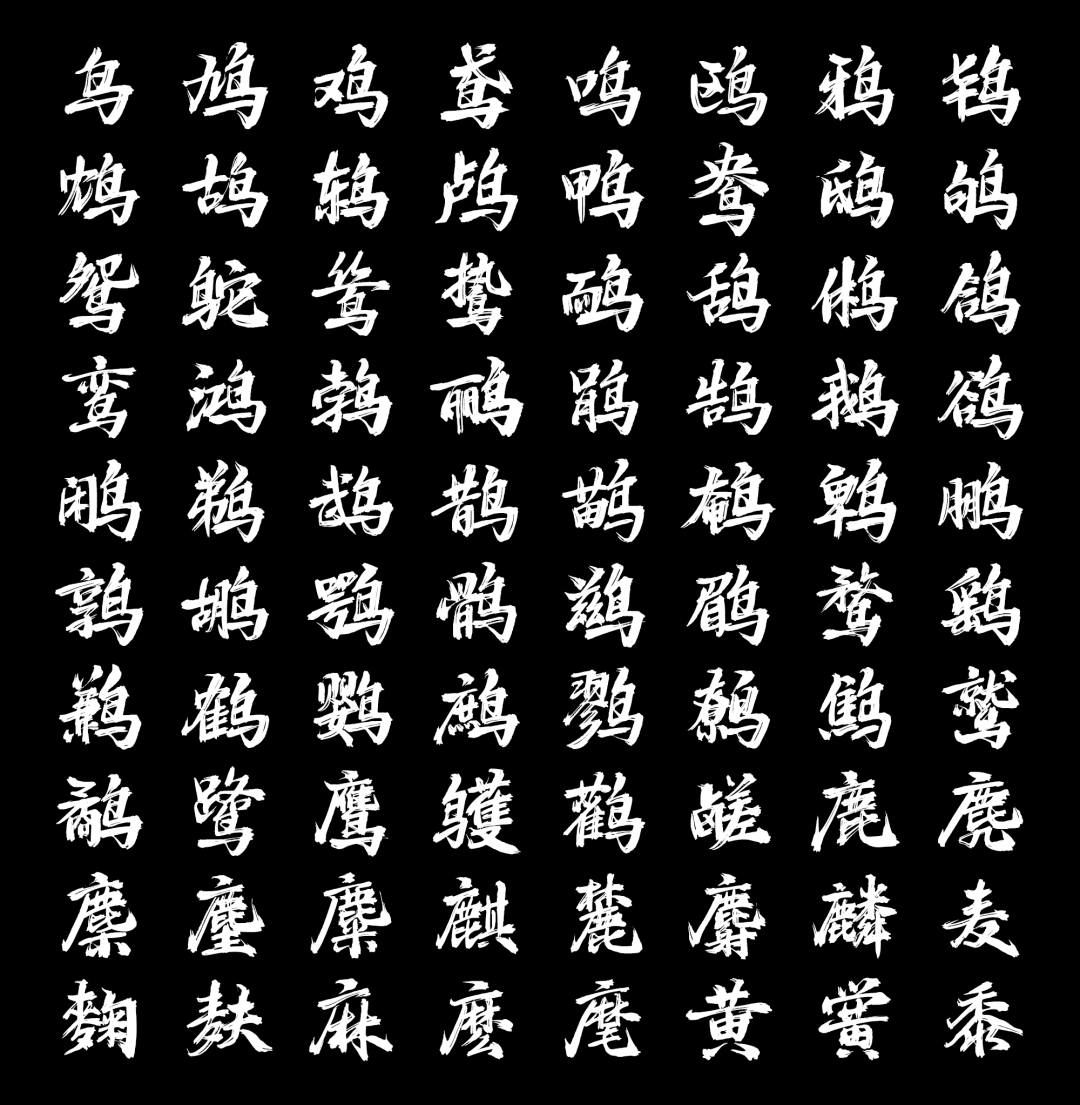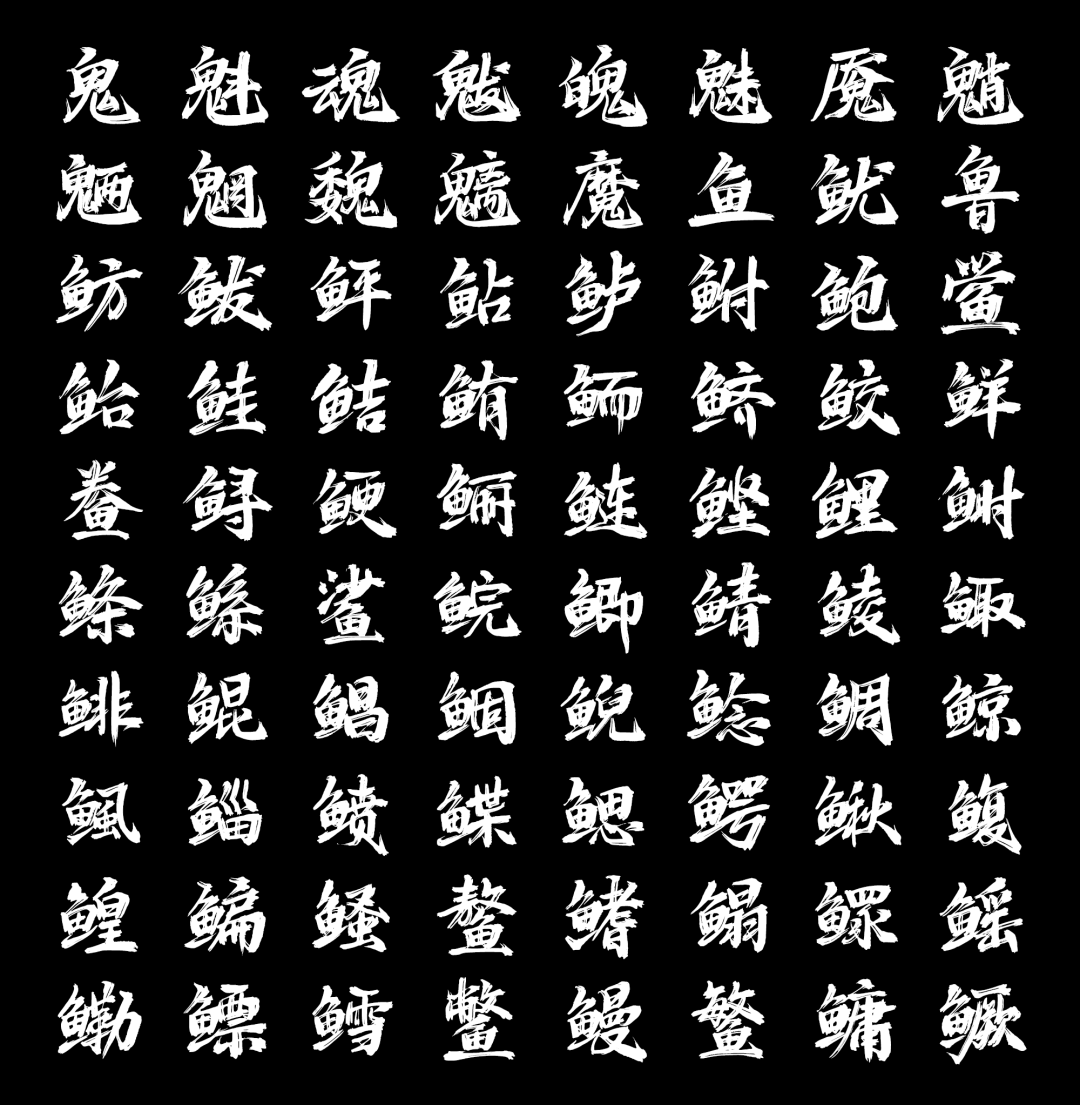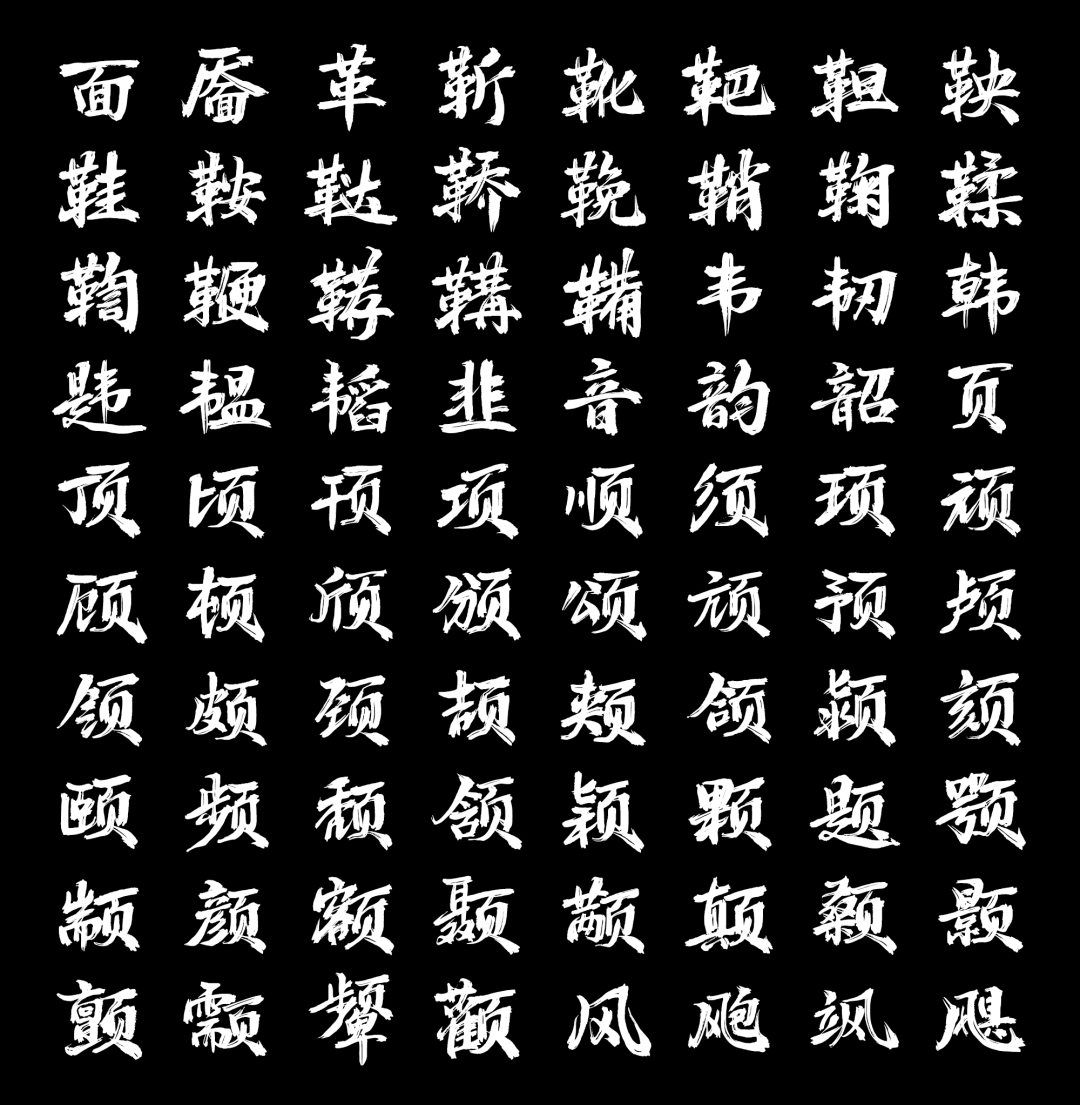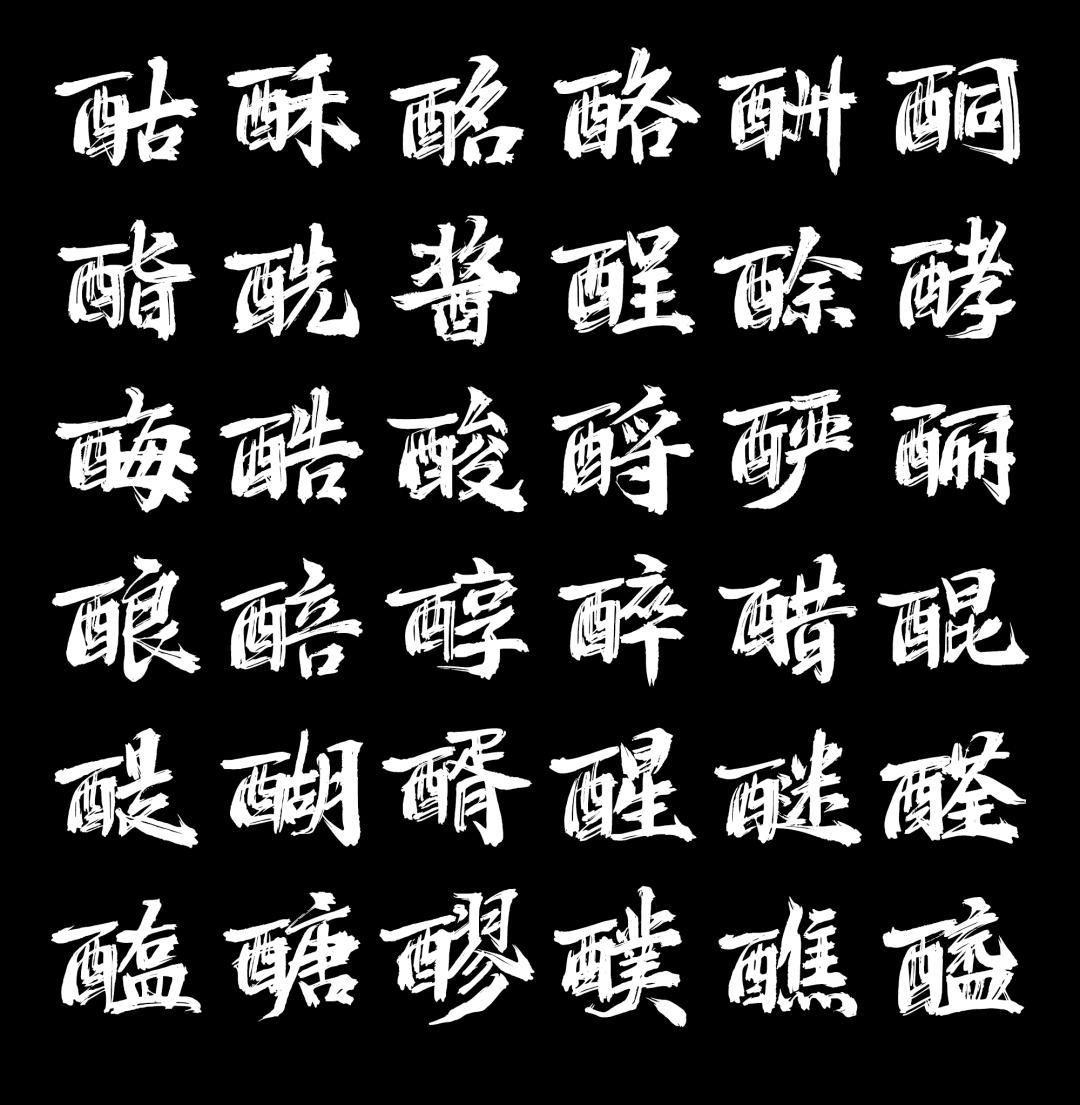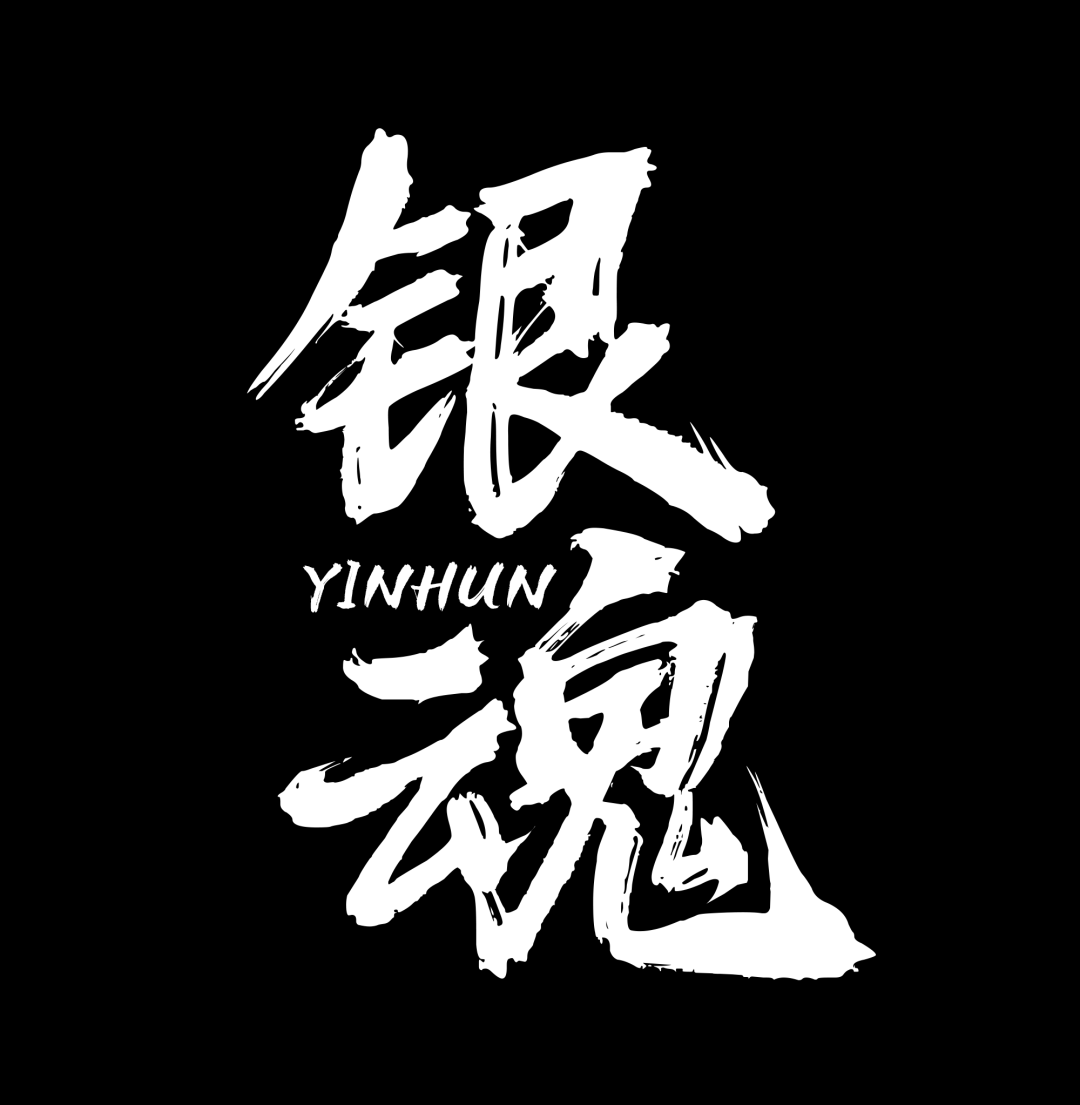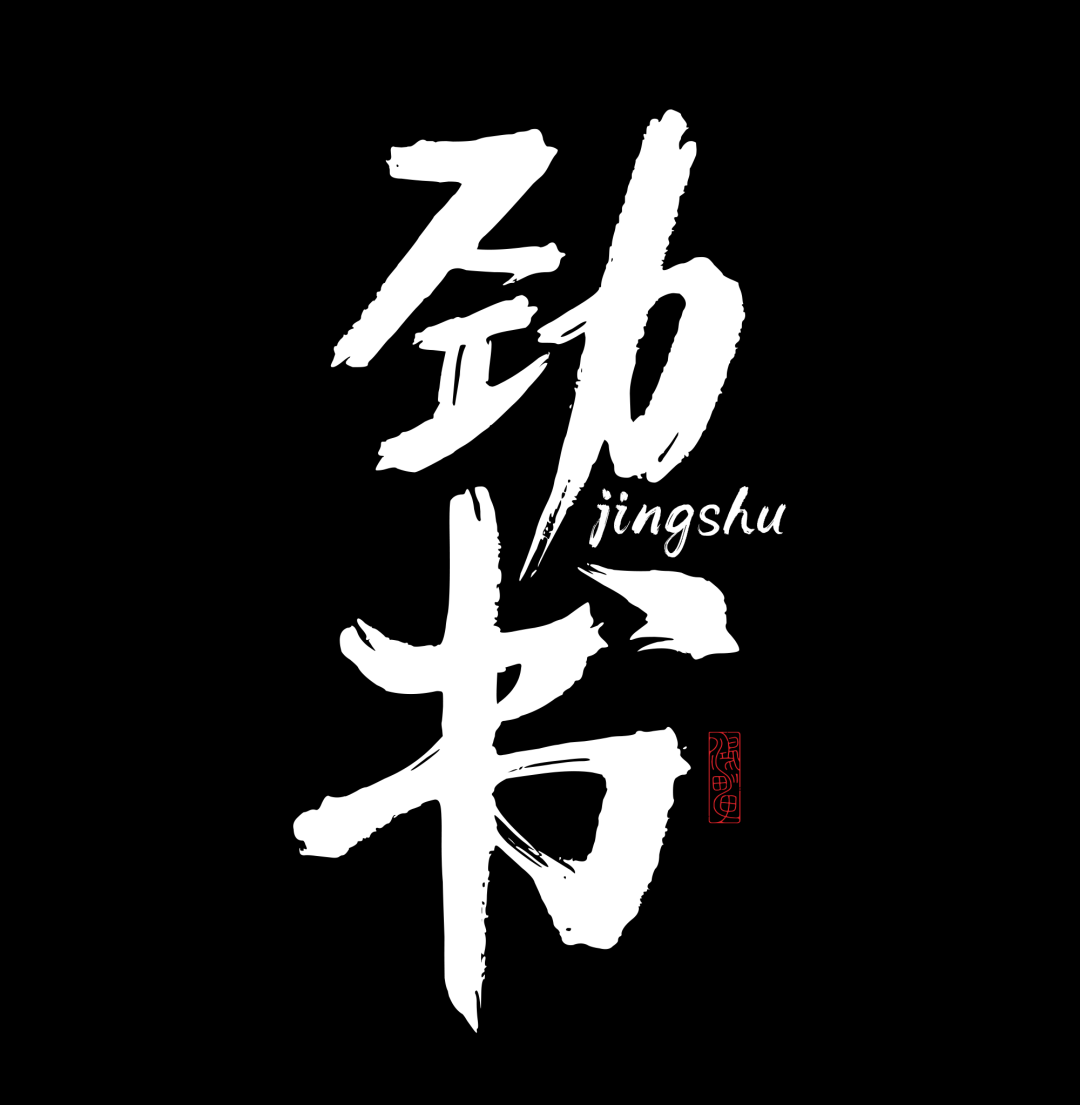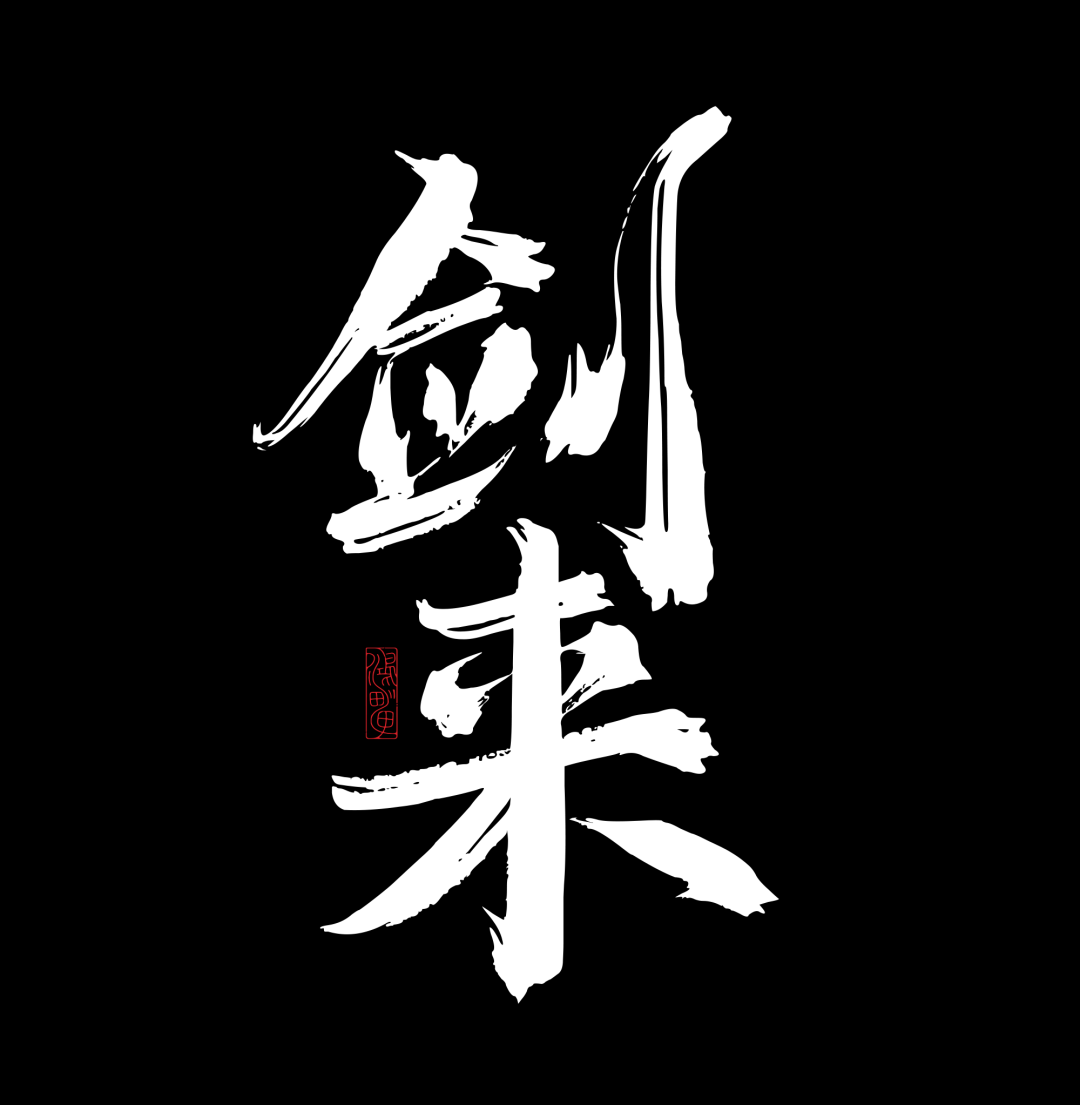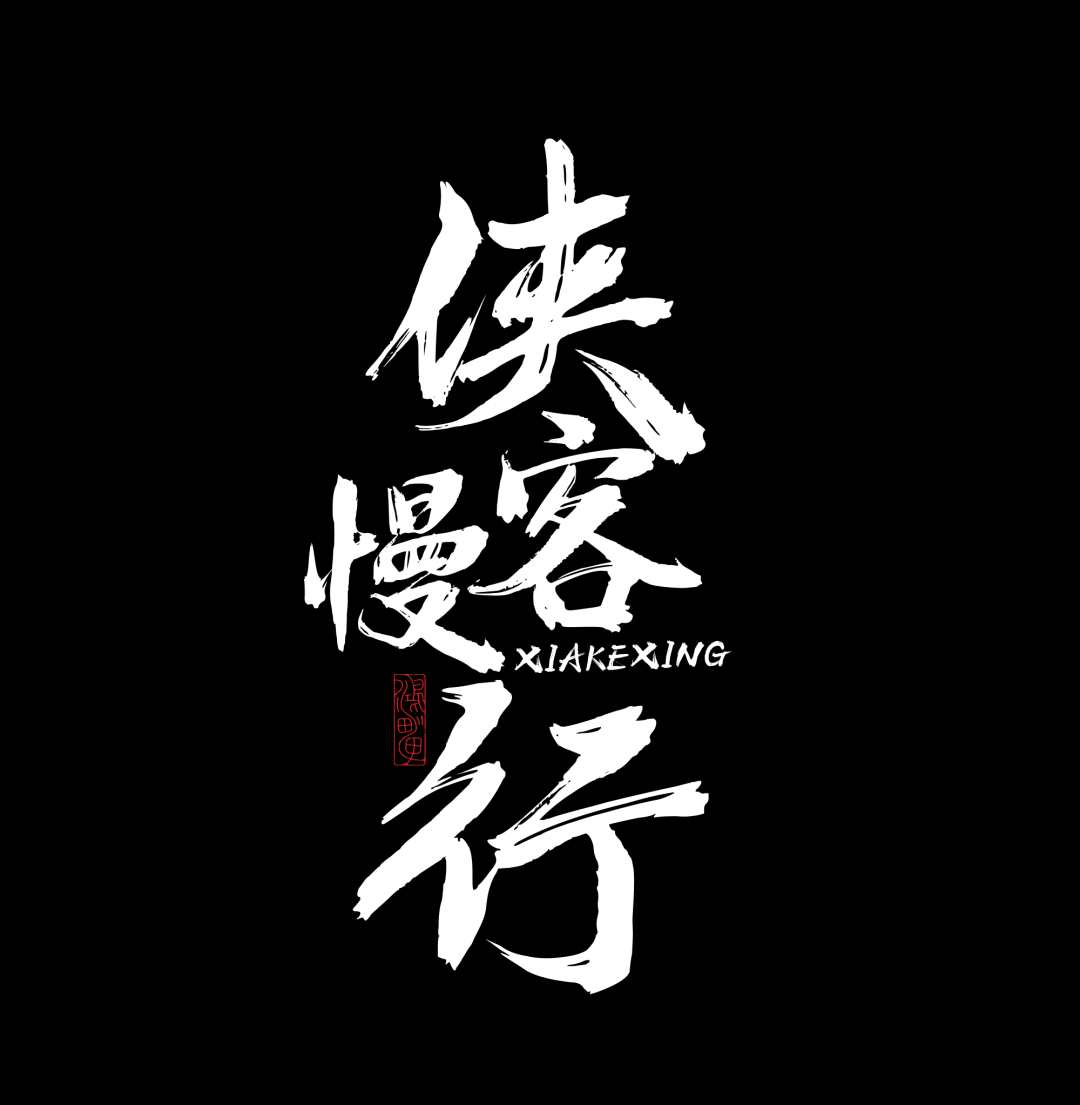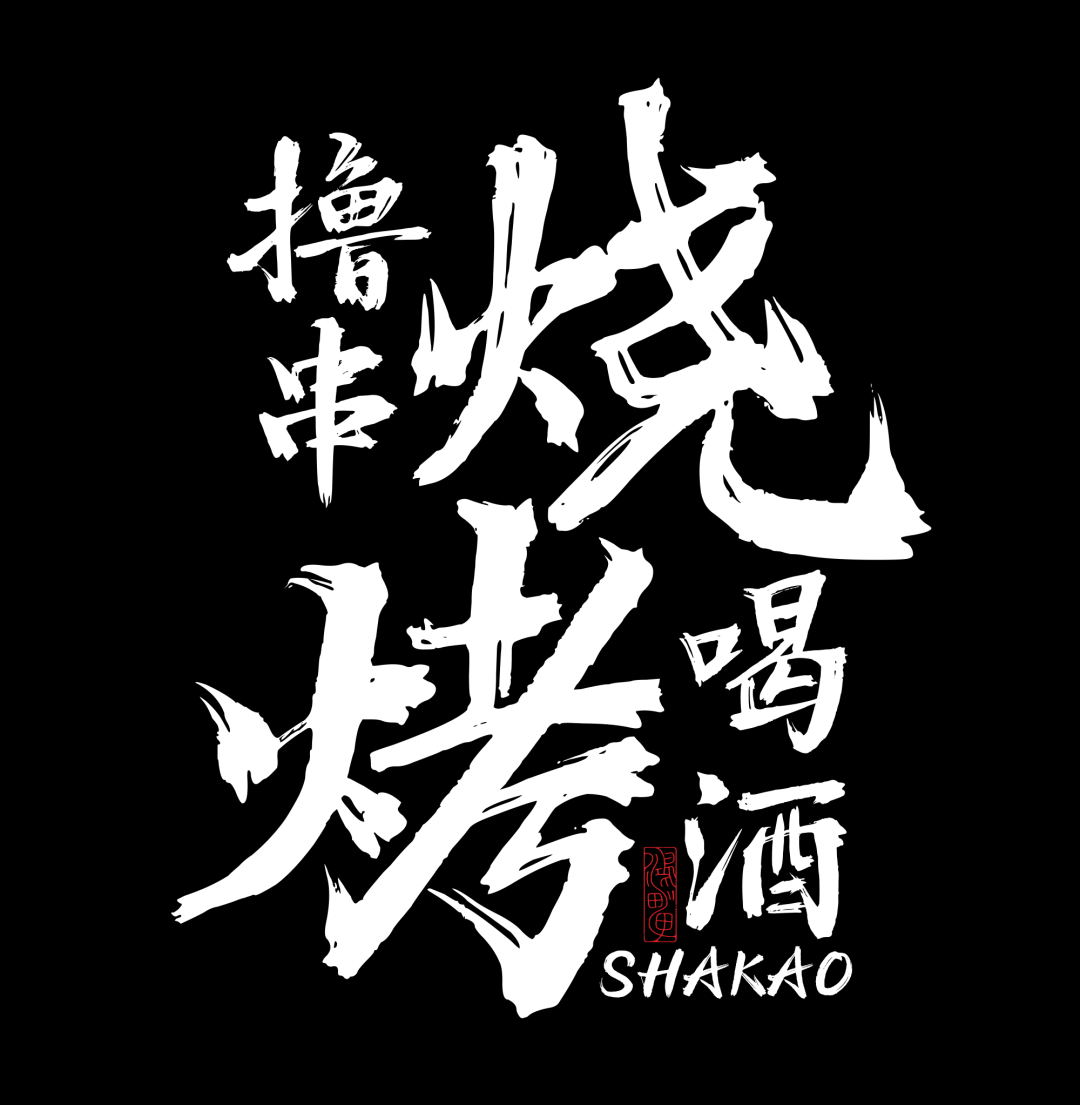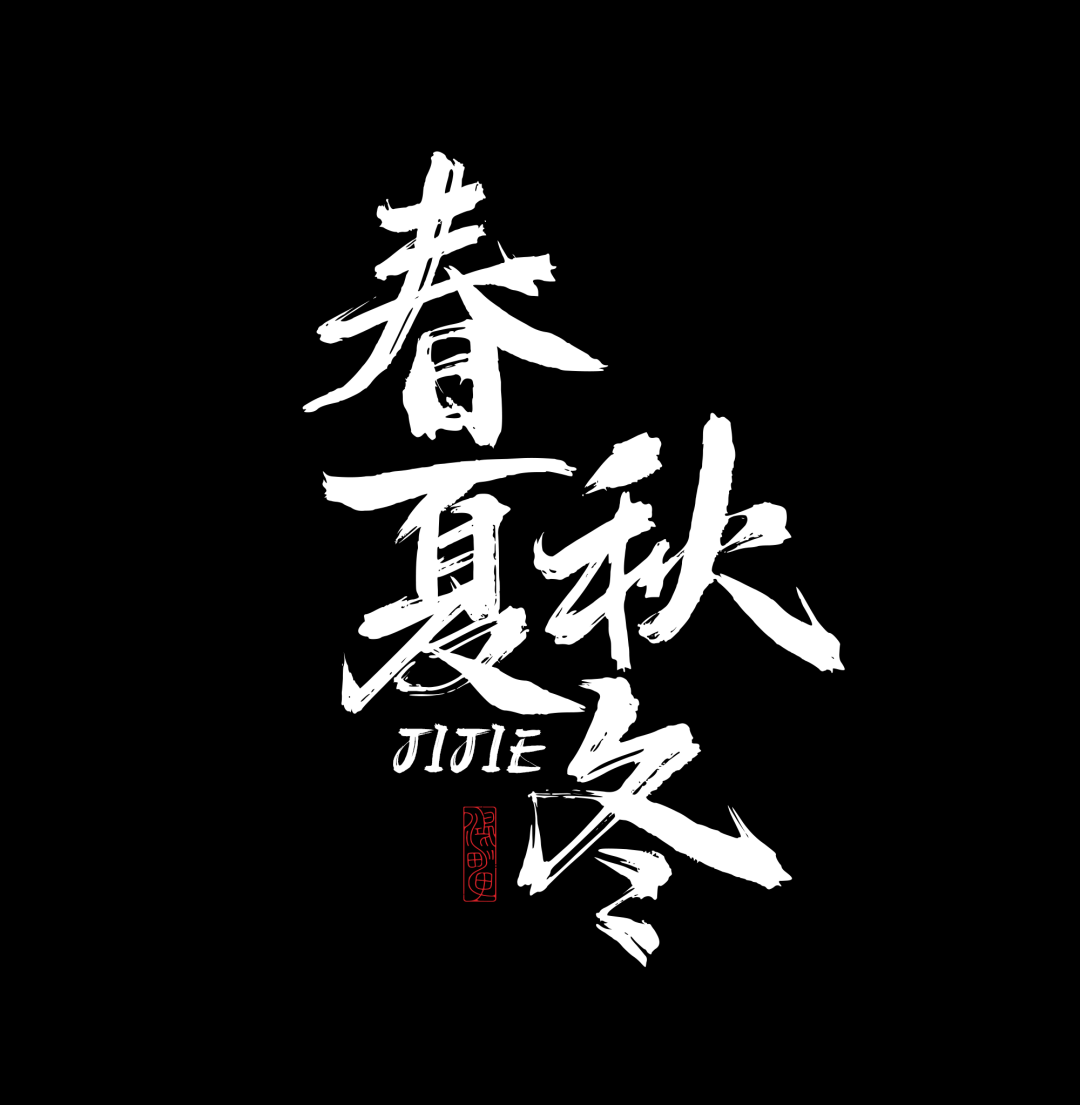
一、字体风格描述
这套字体属于国风毛笔江湖书法体,兼具洒脱随性与文人雅致,整体辨识度高,适配古风、文案、标题类场景:
笔画带有自然飞白、墨痕顿挫、粗细变化,模拟真实毛笔书写的枯笔、浓淡墨色效果,不是刻板电脑规整字体;起笔收笔凌厉利落,撇捺舒展张扬,自带书写的随性动感,无僵硬感。
整体字形开阔大气,结构松散有度,既有江湖书法的狂放不羁、潇洒不羁,又避开粗野戾气;正文字形收敛柔和,适配散文、诗词阅读;标题字(荷塘月色)笔画厚重夸张,张力拉满,可做视觉主标题。
区别于传统工整楷书、端庄宋体,主打自由、写意、随性,自带氛围感;可适配两大方向:一是侠气江湖、刀剑豪情类文案;二是散文、月色、山水类清雅古风内容,刚柔兼备。
毛笔笔锋的纵深感、书卷感会进一步放大,非常适合做古风海报、诗词排版、短视频封面、文创标题。